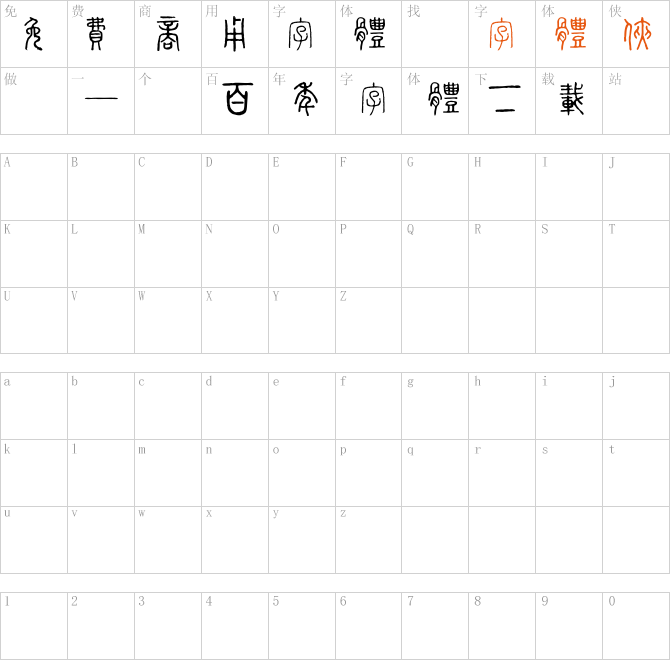
全字库说文解字是一款特别的中文字体,该字体以小篆为风格,古色古香,具有历史的韵味和艺术的美感。其字体设计庄重、个性特色,整体偏梳而下,非常适合用于需要展示文化内涵和历史感的场合。全字库说文解字字体涵盖了广泛的汉字,能够满足各种文本处理和设计需求。
总之,全字库说文解字字体是一款具有独特风格和广泛适用性的中文字体,能够为文本处理和设计带来更多的创意和美感。
全字库说文解字是一款特别的中文字体,该字体采用小篆的风格。
《说文解字》是中国第一部系统地分析汉字字形和考究字源的字书,许慎著,成于安帝建光元年(121年)。原书十四篇,叙目一篇,正文以小篆为主,收9353字,又古文等异体同文1163字,解释十三万余字。
目前采用的版本为艺文印书馆所出版之《说文解字注》,后由南唐徐铉所校定,清代段王裁注之版本(世称大徐本)并参考黎明文化事业公司之《说文解字注》,及南唐徐铉所撰之《说文解字繁传》
由于说文解字原文与现行之Unicode编码并无一完整的对应,因此无法将所有的字形收录于本字体内。以致于会有部分字码无法显示出正确的字形!目前收录于本字体内的字数共6721个字。以 “全字库” 冠名的字体由中国台湾地区的行政机关开发并维护。